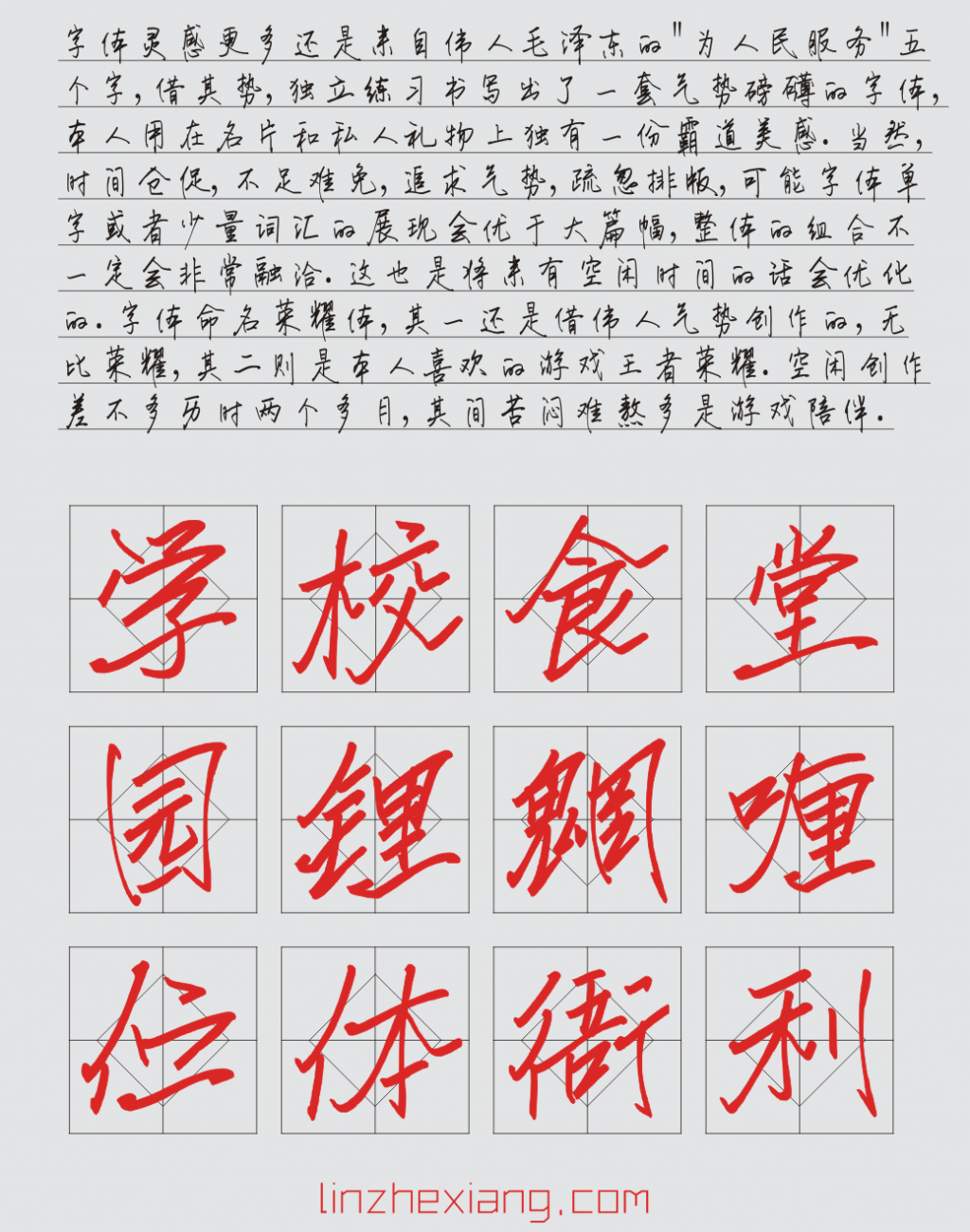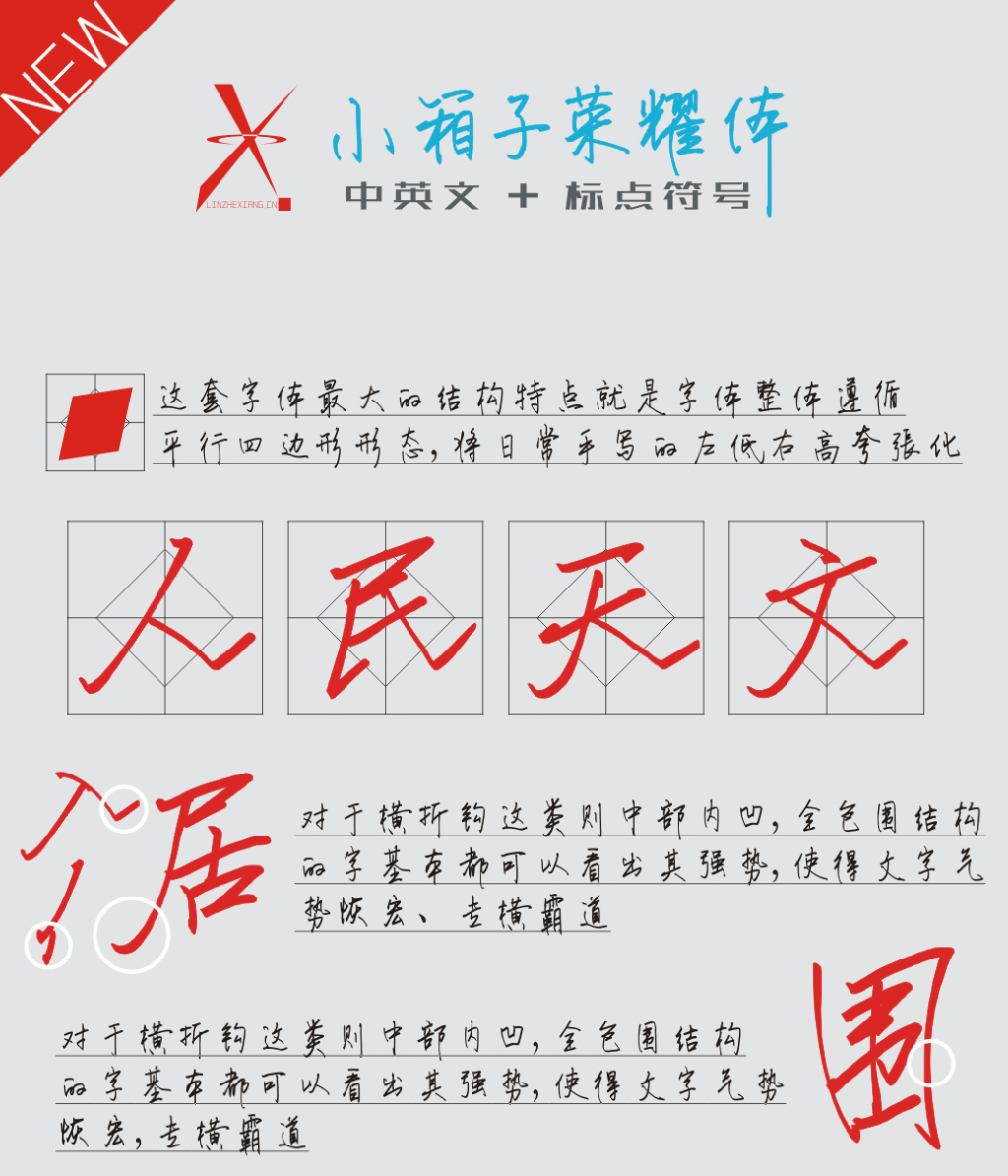
小箱子荣耀体
字体名称: 小箱子荣耀体
字体风格: 个性
这套字体最大的结构特点就是字体整体遵循平行四边形形态,将日常手写的左低右高夸张化,对于横折钩这类则中部内凹,全包围结构的字基本都可以看出其强势,使得文字气势恢宏,专横霸道。
字体灵感更多还是来自伟人毛泽东的”为人民服务”五个字,借其势,独立练习书写出了一套气势的字体,本人用在名片和私人礼物上独有一份霸道美感.当然,时间仓促,不足难免,追求气势,疏忽排版,可能字体单字或者少量词汇的展现会优于大篇幅,整体的组合不一定会非常融洽.这也是将来有空闲时间的话会优化的.字体命名荣耀体,其一还是借伟人气势创作的,无比荣耀,其二则是本人喜欢的游戏王者荣耀。
小箱子荣耀体”是一款书写很新颖的字体,字体大方,适合各种设计作品使用!欢迎下载!